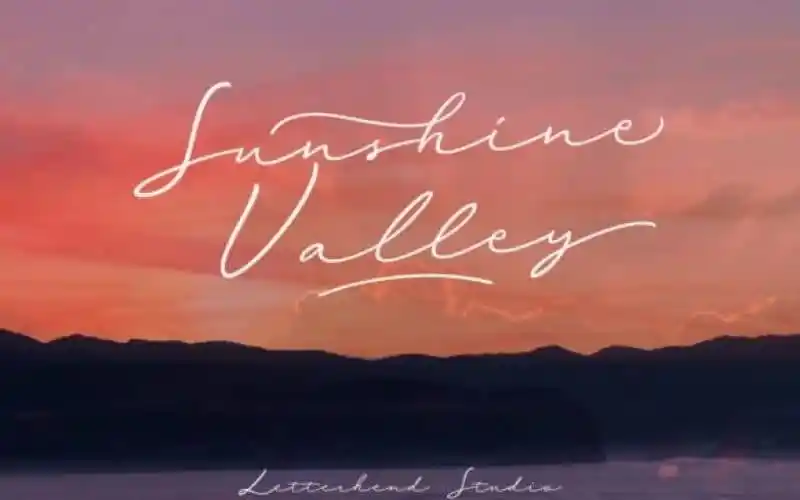
A Sunshine Valley Handwritten Font é uma elegante tipografia escrita à mão desenvolvida pelo Letterhend Studio. Ela se destaca por suas formas delicadas e curvas arredondadas, características inerentes a qualquer guion. Ideal para designers que buscam um toque autêntico em designs como cartões de casamento, cartões de agradecimento, mensagens pessoais, selos de cartão, logotipos e cards de negócios, essa fonte oferece uma paleta sofisticada de opções para complementar seu trabalho. Seja para um projeto que exige uma mão humana ou simplesmente desejando um toque refinado em sua arte digital, Sunshine Valley Handwritten Font é a escolha perfeita para aqueles buscando algo único e autêntico.